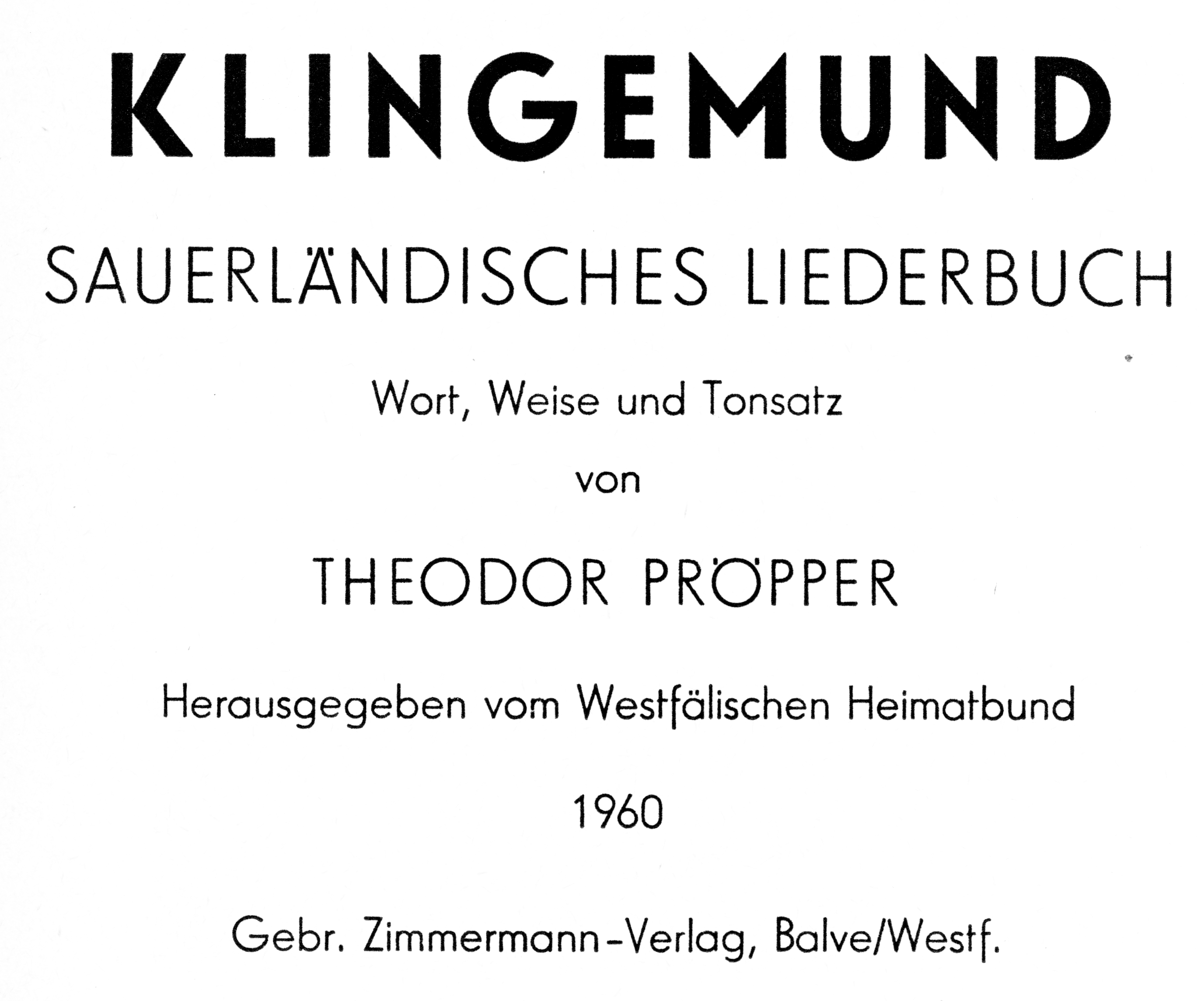
Suche Schrift dieses „Heimat“-Buches von 1960 (Klingemund)
gesucht werden die beiden Schnitte dieser schlanken Grotesken. Im Fließtext wurde von dem Verlag gerne die Neuzeit Grotesk verwendet. Die passt hier allerdings nicht. Die Futura-Varianten, die ich kenne, passen auch nicht komplett (der reguläre Schnitt ist zu breit, der schmale zu schmal); vielleicht eine noch nicht digitalisierte Variante?
WhatFontIs spuckte nur moderne Schriften aus, die sich deutlich unterscheiden.
Battling Medium.
Relish Pro.
Windlesham Pro Bold.
Guildford Pro Bold.
Danke, Bertel. In der Richtung suche ich gerade auch, die haben aber alle den schrägen Strich beim kleinen e, was mich vorschnell denken ließ, dass es die nicht sind.
Die Vorlage Elegant Grotesque von Hans Möhring hat den geraden e-Strich. Warum baut man ausgerechnet bei diesem Buchstaben eine doch recht markante Änderung ein.
Und die Umlautpunkte der Versalien passen auch nicht... :cry:
Das ist relativ normal. Die früheren Bleisatzschriften waren für den lokalen Einsatz in deutscher Sprache bestimmt und zogen die Umlautpunkte ein, da man ja nichts über dem oberen Kegelende platzieren konnte. Digitalisierungen haben das Problem nicht mehr und setzen die Umlautpunkte eher passend zu den anderen diakritischen Zeichen. Bestenfalls gibt es die eingezogenen Punkte als OpenType-Variante.